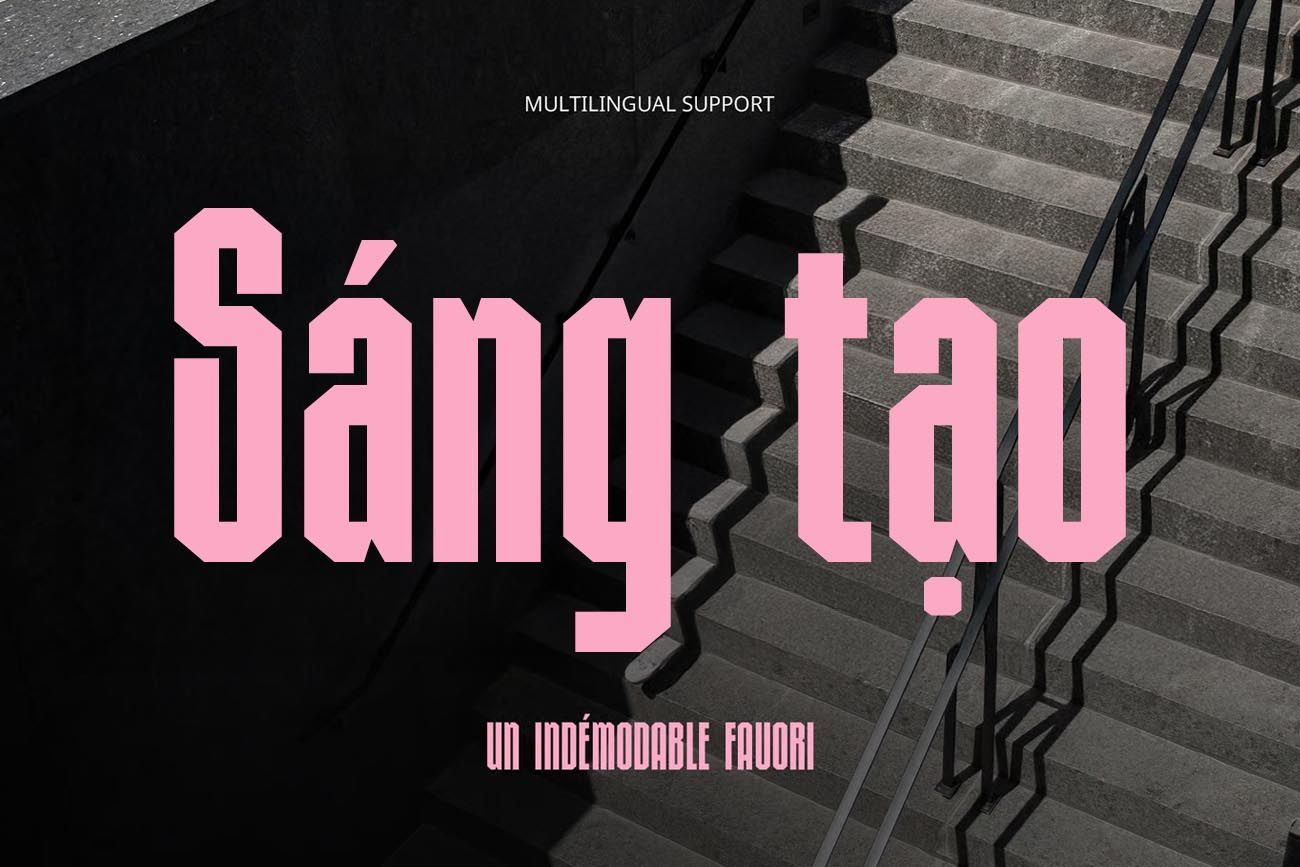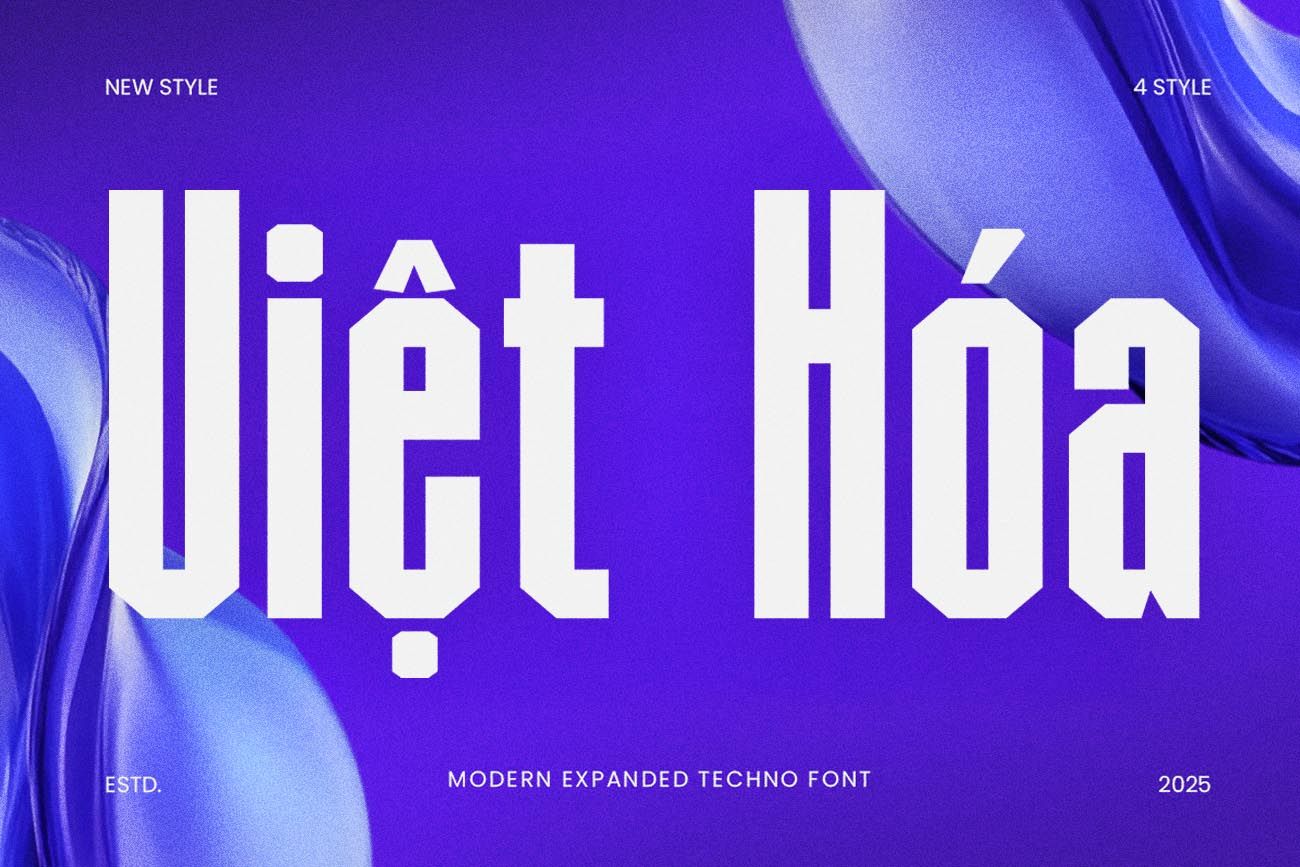
![[Tải xuống] TOP 11+ Font chữ cứng cáp Việt hóa cho thiết kế năm 2025](https://cdn.s99.vn/blog/cung-cap-11111.jpg)
Những font chữ cứng cáp thường được thiết kế với những đường nét chắc chắn, góc cạnh và mạnh mẽ, tạo nên một cảm giác vững vàng và quyết đoán. Chính vì vậy, chúng thường được sử dụng trong các tựa game hành động, đua xe, bóng đá, hay thậm chí là trong các sự kiện thể thao thế giới. Những font chữ cứng cáp không chỉ là một phần của thiết kế, mà còn là biểu tượng của sức mạnh, tốc độ và sự quyết đoán.
Font chữ TH Wosker là một kiểu chữ display siêu đậm, thiết kế với các đường nét vuông vức, góc cạnh mạnh mẽ, mang lại cảm giác cứng cáp và dứt khoát. Các ký tự được tối ưu hóa để tạo nên ấn tượng mạnh về mặt thị giác, lý tưởng cho tiêu đề, logo, poster và thiết kế quảng cáo. Phong cách hiện đại kết hợp với kết cấu hình học khiến Wosker trở thành lựa chọn nổi bật trong các dự án đậm chất cá tính.
Font được thiết kế bởi LMNTYPE, phát hành năm 2024. Phiên bản tiếng Việt đã được Việt hóa đầy đủ bởi Phạm Sơn – Admin S99.vn & Fontdep.vn.
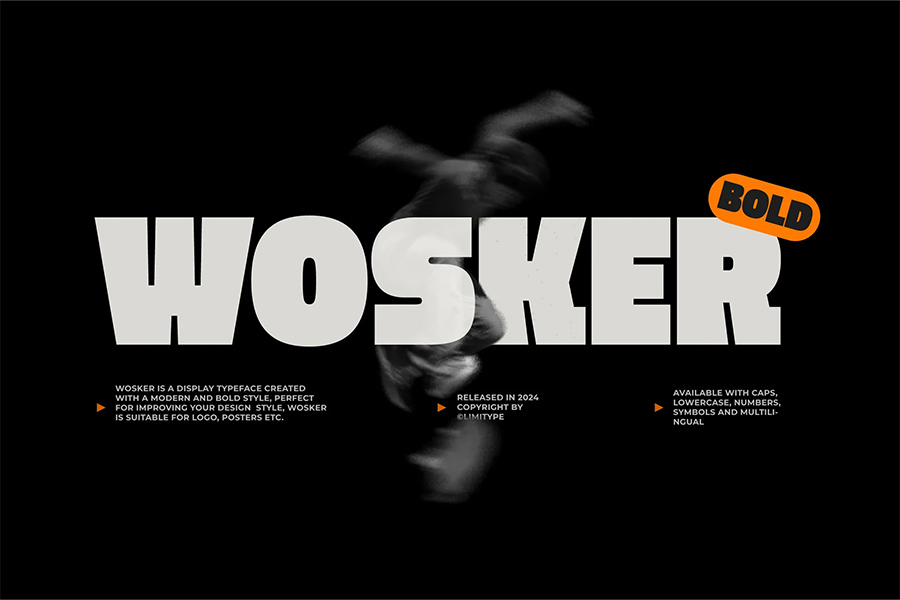
Edge of the Galaxy là một font chữ cứng cáp việt hóa mang phong cách thể thao hiện đại. Với các đường nét sắc sảo và thiết kế dứt khoát, font tạo cảm giác tốc độ và sức mạnh – rất phù hợp cho tiêu đề game, poster eSport hoặc logo giải đấu. Đây là một font chữ mạnh mẽ giúp thu hút thị giác và thể hiện tinh thần chiến đấu ngay từ cái nhìn đầu tiên. Font chữ được Việt hóa bởi Font Zin.
Font chữ TH Hagsub có thiết kế rất đặc biệt, mang đến một cảm giác vừa hiện đại vừa sang trọng. Với các đường nét mềm mại nhưng vẫn đủ mạnh mẽ để tạo điểm nhấn, TH Hagsub là lựa chọn lý tưởng cho các dự án thiết kế chuyên nghiệp như logo, tiêu đề bài viết hoặc quảng cáo. Font này giúp các thông điệp trở nên rõ ràng và dễ tiếp cận, đặc biệt phù hợp với các lĩnh vực yêu cầu sự tinh tế như thời trang, mỹ phẩm hoặc các thương hiệu cao cấp.
4. Font chữ thể thao TH Cungcap 1 - Đậm, mạnh mẽ & Việt hóa
TH Cungcap 1 là một font chữ cứng cáp hiện đại, sở hữu các nét chữ chắc chắn, thẳng và rõ ràng. Thiết kế đậm nét giúp font dễ đọc, chuyên nghiệp nhưng vẫn đủ cá tính để nổi bật trong quảng cáo, tiêu đề web hoặc thiết kế thương hiệu. Nếu bạn đang tìm một font chữ mạnh mẽ cho dự án công nghệ hay doanh nghiệp, TH Cungcap 1 là lựa chọn không nên bỏ qua.
Font chữ được Việt hóa bởi Phạm Sơn - Admin S99.VN và Fontdep.vn
Font TH Kagami nổi bật với phong cách tối giản nhưng tinh tế, mang đến sự dễ dàng tiếp cận và sự thanh thoát trong từng đường nét. Đây là lựa chọn tuyệt vời cho các thiết kế cần sự sang trọng nhưng vẫn giữ được vẻ hiện đại. Kiểu chữ này rất phù hợp cho các dự án thiết kế website, logo, brochure hoặc thậm chí là các tiêu đề trong các bài viết hay bài báo.
6. Font Mạnh Mẽ TH Gymaxy – Cơ Bắp, Hình Khối & Việt Hóa
Lấy cảm hứng từ thể hình và sức mạnh cơ bắp, TH Gymaxy là một font chữ cứng cáp Việt hóa nổi bật với kiểu dáng hình khối mạnh mẽ, vuông vức và dứt khoát. Font lý tưởng cho tiêu đề lớn, poster sự kiện, logo thể thao hoặc các dự án branding cá tính. Đây là một trong những font chữ mạnh mẽ thể hiện rõ tinh thần thể thao và quyết tâm.
7. Font chữ cứng cáp, mạnh mẽ TH Striger
Font TH Striger là một trong những font chữ mạnh mẽ nhất dành cho các thiết kế liên quan đến thể thao và game. Với các đường nét sắc bén và sự kết hợp giữa các yếu tố mạnh mẽ và tốc độ, Striger mang đến cảm giác năng động và đầy sức sống. Font này phù hợp với các dự án thiết kế game thể thao, thể thao điện tử hoặc bất kỳ lĩnh vực nào cần thể hiện sự mạnh mẽ và quyết liệt.
TH Renoric là một font chữ cứng cáp mang phong cách thể thao hiện đại, dễ đọc và dễ áp dụng trong nhiều loại thiết kế. Với các nét thẳng, sắc gọn và tỷ lệ cân đối, font phù hợp để dùng trong poster game, tiêu đề quảng cáo, hoặc banner sự kiện. Đây là một font mạnh mẽ giúp truyền tải thông điệp rõ ràng và chuyên nghiệp, đồng thời tạo điểm nhấn cho thiết kế.
Font Bladus Slant mang đến một cảm giác tốc độ và sự chuyển động mạnh mẽ nhờ vào thiết kế nghiêng đặc biệt. Font này là sự lựa chọn lý tưởng cho các dự án liên quan đến thể thao, xe cộ, game đua xe hoặc bất kỳ sản phẩm nào cần thể hiện sự nhanh nhẹn và quyết liệt. Với các đường chéo mạnh mẽ, Bladus Slant không chỉ dễ đọc mà còn tạo ra cảm giác động lực và tốc độ. Đây là font chữ lý tưởng cho các tiêu đề hoặc banner muốn thể hiện sức mạnh và sự năng động.
10. Font chữ mạnh mẽ, hiện đại Việt hóa TH Kairo
Font TH Kairo là một sự kết hợp giữa phong cách mạnh mẽ và hiện đại, mang đến cho các thiết kế của bạn một vẻ đẹp sắc sảo và dễ tiếp cận. Các đường nét đơn giản nhưng rõ ràng giúp font này dễ dàng áp dụng trong các dự án như logo, website hay các quảng cáo ngoài trời. Font Kairo là sự lựa chọn lý tưởng cho những ai cần tạo ra một hình ảnh mạnh mẽ nhưng vẫn có tính thẩm mỹ cao.
Trên đây là tuyển tập những font chữ cứng cáp Việt hóa nổi bật nhất dành cho các nhà thiết kế yêu thích phong cách mạnh mẽ, hiện đại và quyết đoán. Dù bạn đang thực hiện một dự án game hành động, banner thể thao, hay xây dựng bộ nhận diện thương hiệu cá tính – những font chữ này chắc chắn sẽ giúp thiết kế của bạn trở nên ấn tượng hơn.